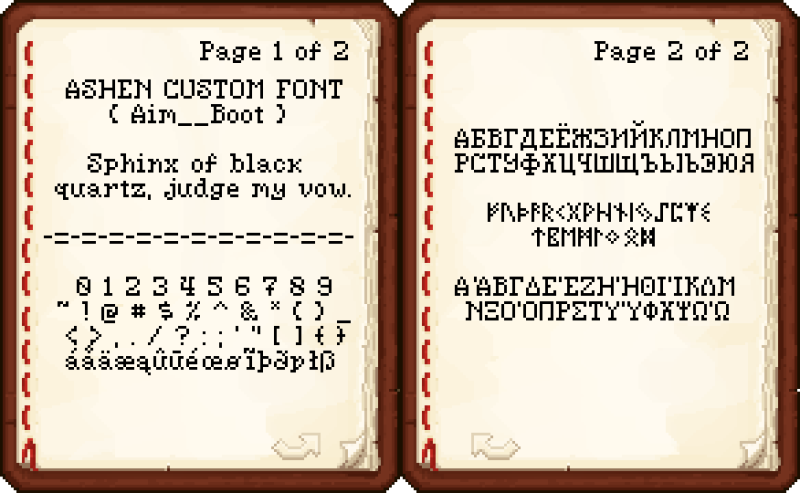
Ashen 16x Custom Font 1.21.5/1.19.2 (шрифт, средневековый, фэнтези, 16x 16x)
Ashen 16x Custom Font — это отдельный набор шрифтов, созданный специально для текстурпака Ashen 16x, но совместимый с любыми другими ресурспаками. Шрифт выполнен в средневеково-фэнтезийном стиле с засечками и полностью заменяет стандартный шрифт Minecraft.
В отличие от многих других наборов шрифтов, этот охватывает не только латиницу, но и все символы, которые можно ввести в ванильном Minecraft, включая алфавиты разбойников и Стандартный Галактический (алфавит стола зачарования). Исключение составляют символы Юникода, например, деванагари — они не переопределяются.